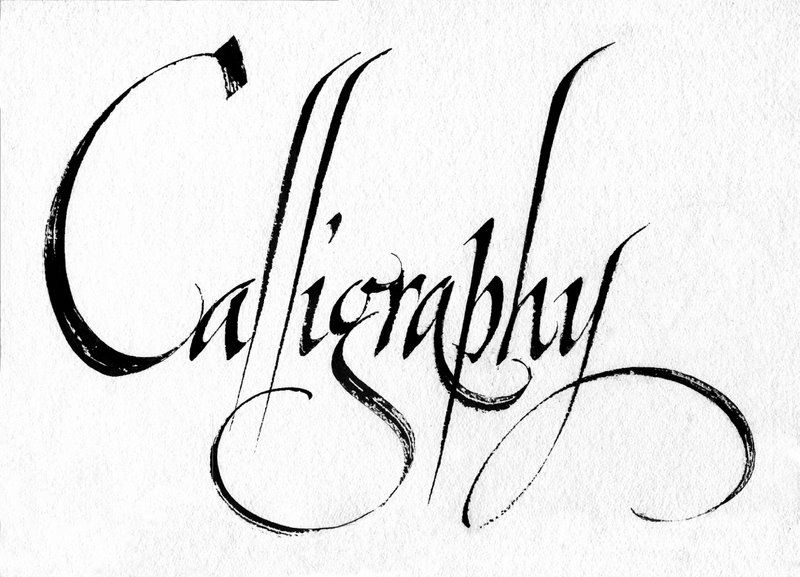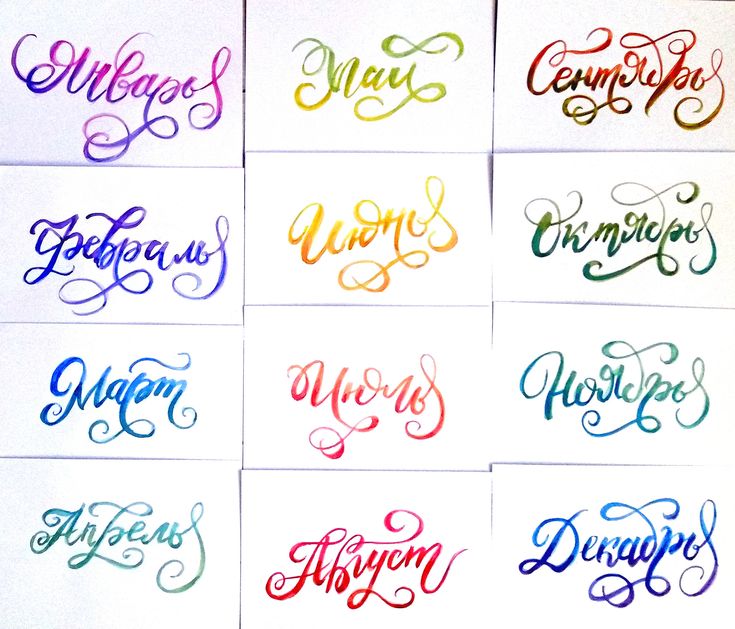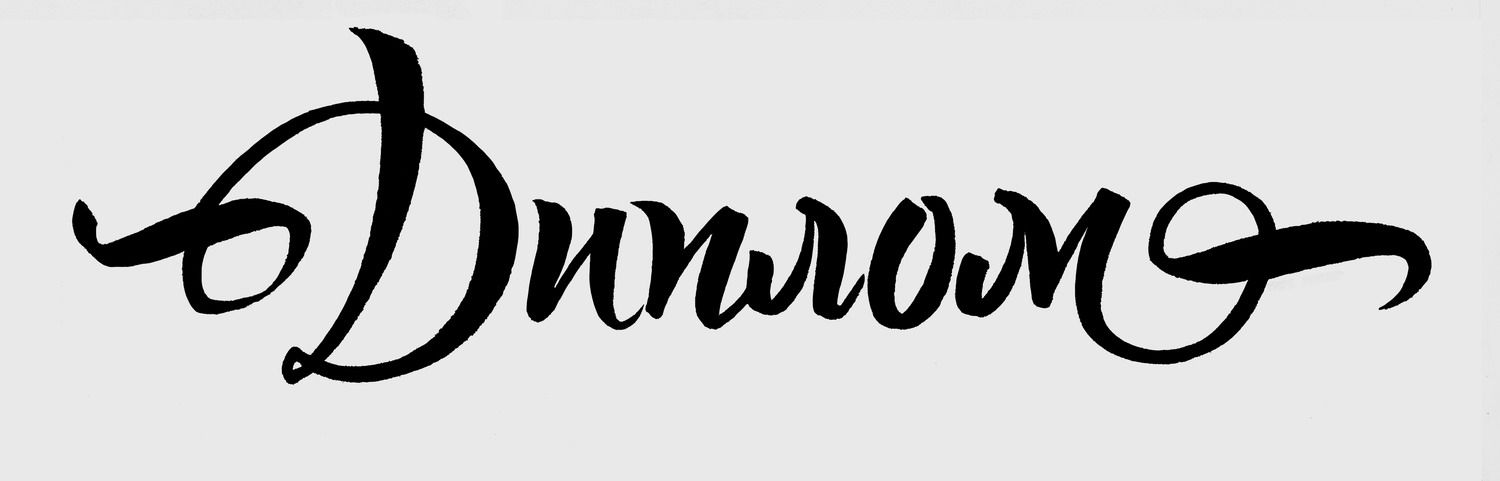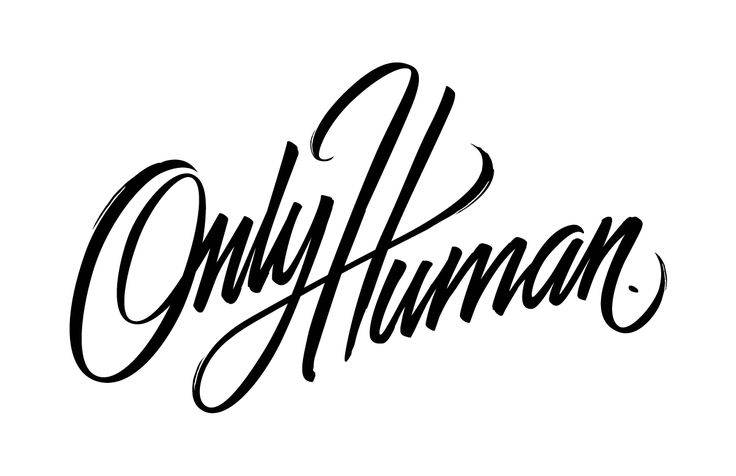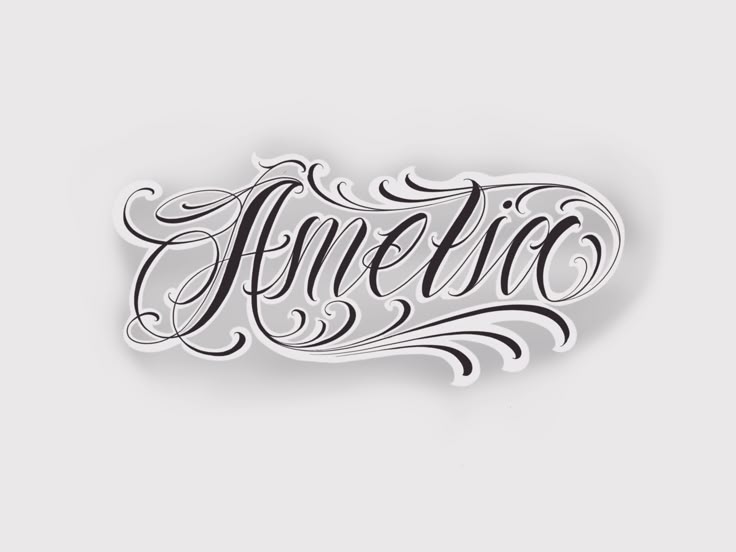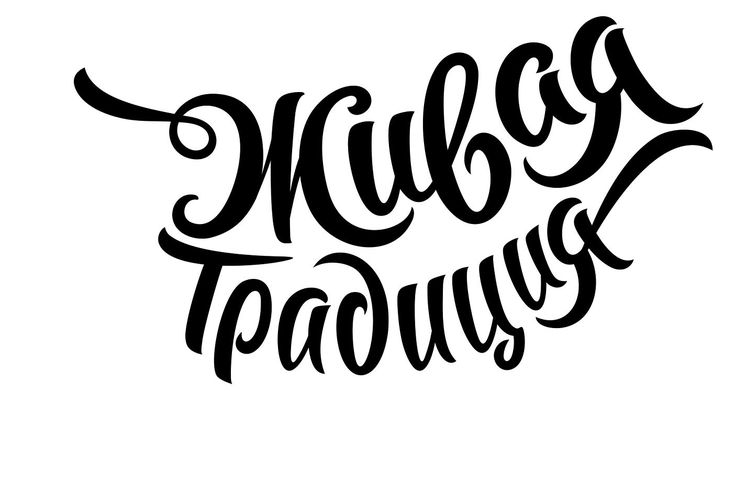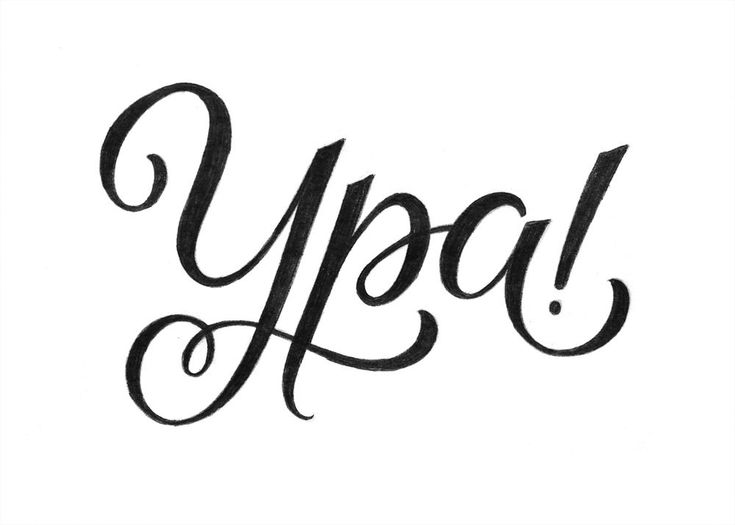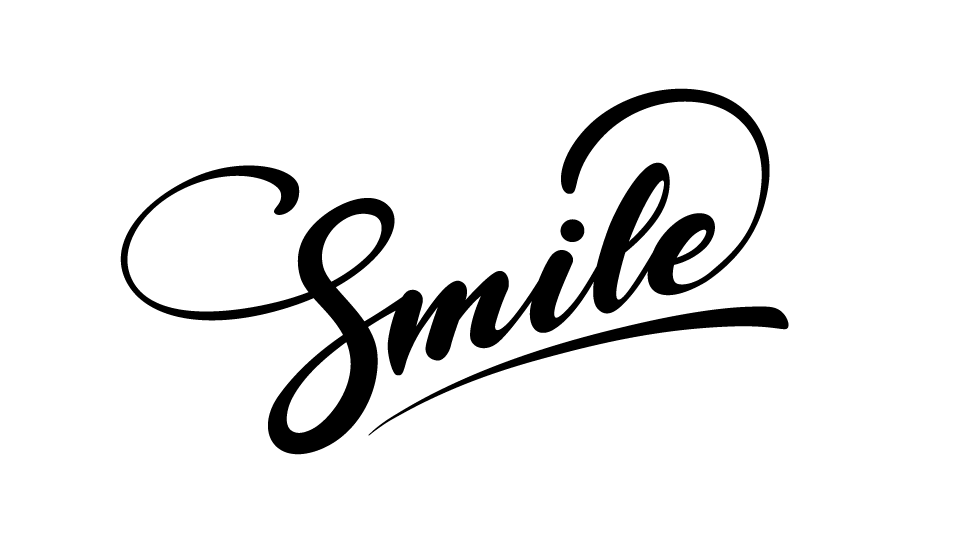
Надпись шрифтом: Красивые шрифты онлайн | Написать текст и скопировать
Красивые шрифты онлайн ✬ Написать и скопировать 😍
Интерес и лояльность пользователей в соцсети Инстаграм эквивалентны подписке на интересующего человека. Но для того, чтобы привлечь фолловеров, нужно выделяться. Например, с юмором рассказывать о себе, постить интересные фото, видео с прикольным описанием. А если аккаунт предусмотрен для коммерческих целей? Тогда отличиться от остальных будет сложнее. Ведь существующие инструменты в Инстаграм – достаточно простые, негибкие и, прямо скажем, скучные. Тогда как же заинтересовать потенциального подписчика?
Необычный шрифт вам в помощь!
Чтобы обратить внимание на свой инста-профиль, нужно не просто запостить красивую картинку, но и применить к ней оригинальный шрифт – написать красивыми буквами небольшую фразу.
Эта уловка может не просто привлечь пользователя, сделать его вашим подписчиком, но и сподвигнуть написать вам с личной или бизнес-целью.
Генератор шрифтов сделает Instagram-аккаунт уникальным, выделит его среди других. Этот прием наиболее часто используется SMM-специалистами для привлечения внимания пользователей Инстаграм. К сожалению, Instagram не располагает возможностью редактирования шрифтов. Однако у нас есть хорошая альтернатива. Мы предлагаем воспользоваться нашей онлайн-платформой для всех желающих сделать свой аккаунт максимально оригинальным.
Самые распространенные шрифты
Любители написать красивыми буквами уже определились с фаворитами среди beautiful fonts. Предлагаем попробовать и вам оценить наши шрифты для ников, среди которых вы найдете:
- необычные курсивы, жирные шрифты;
- буквы в обрамлении кружочков, дужек;
- интуитивно понятные слова символами, рисунками или геометрическими фигурами;
- шрифты в греческом, английском стиле;
- пузырьковые, контурные и готические буквы;
- буквы в обрамлении различных символов.
Написать красивым шрифтом онлайн и скопировать текст на русском языке бесплатно и вставить можно в любые поля страницы соцсети Инстаграм: «О себе», «Подпись к фото», «Комментировать» и т.д.
Если хотите иметь еще более необычную подпись, у нас вы можете воспользоваться обрамлением текста слева и/или справа в виде оригинальных и необычно расположенных символов.
Будь то английский шрифт красивый, готический, пузырьковый или рождественский, изменить серый скучный текст в любимой соцсети Instagram еще никогда не было так просто. Тем более что красивые шрифты для инстаграма можно копировать и использовать бесплатно в любом необходимом количестве. Используйте безграничные возможности нашей онлайн платформы, чтобы быть абсолютно уникальными с новыми подборками буквенно-символьных шрифтов!
Как приложение работает
- Загрузите одно фото с вашего компьютера, Google Drive или Dropbox.
Это можно сделать, перетащив фото в приложение или кликнув на «Выбрать изображение». Добавьте текст или логотип, который можно загрузить с компьютера, Google Drive или Dropbox. - С помощью набора инструментов для редактирования стилизуйте свой текст или логотип так, как вам захочется. Чтобы поменять положение текста, не нужно вводить количество пикселей. Кликните по нему и перетащите в любое место на фотографии. Всё просто и доступно.
- Нажмите «Сохранить изображение» и загрузите копию своего фото с текстом или логотипом.